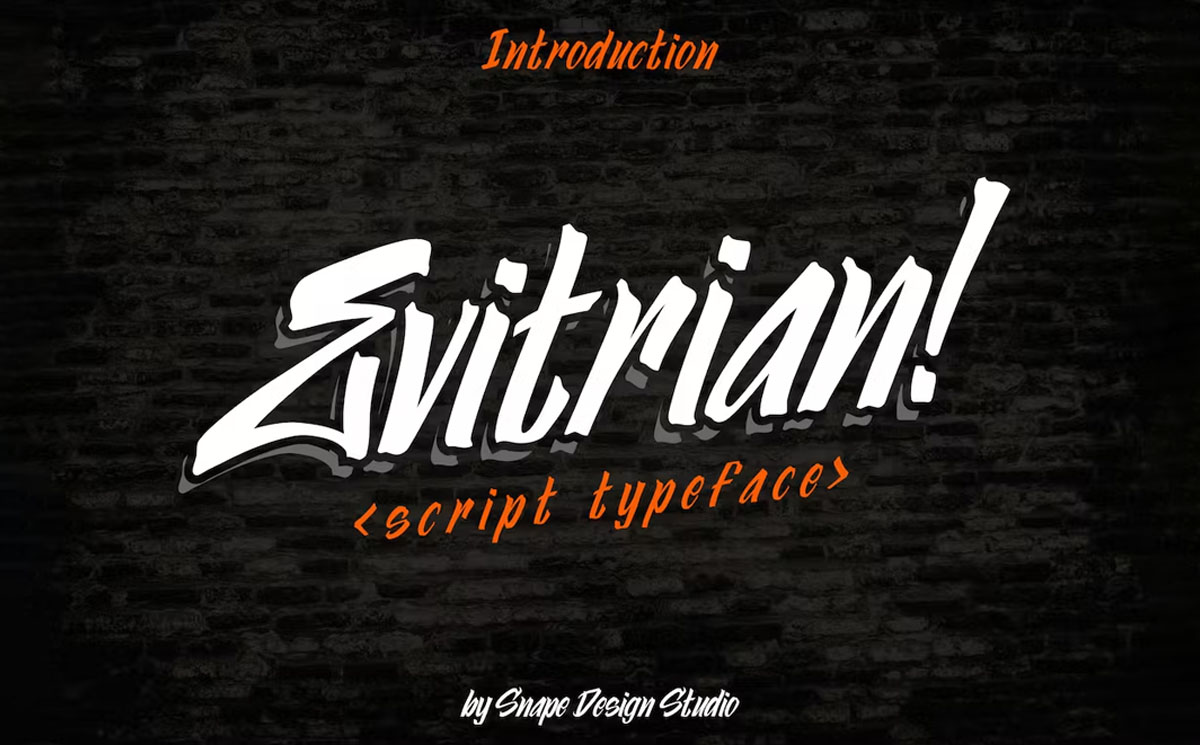
Phông chữ hiphop Việt hóa SVN Evitrian
Phông chữ HipHop Việt hóa SVN Evitrian – Cá tính, mạnh mẽ và đậm chất đường phố
Nếu bạn đang tìm kiếm một font chữ mang phong cách HipHop, Graffiti và Street Art, SVN Evitrian Việt hóa là lựa chọn rất đáng thử. Bộ font gây ấn tượng với những đường nét mạnh, phá cách và giàu năng lượng, phù hợp cho các thiết kế cần tạo cảm giác nổi bật ngay từ cái nhìn đầu tiên.
SVN Evitrian – Font chữ đậm chất HipHop đường phố
SVN Evitrian sở hữu phong cách typography cá tính với các nét chữ độc đáo, mang hơi hướng HipHop, Urban và văn hóa đường phố. Kiểu dáng chữ mạnh mẽ giúp thiết kế trở nên trẻ trung, nổi loạn và có chất riêng hơn so với những font thông thường.
Phiên bản SVN Evitrian Việt hóa hỗ trợ tiếng Việt đầy đủ, giúp designer dễ dàng sử dụng các dấu tiếng Việt mà vẫn giữ được phong cách nguyên bản của font.
SVN Evitrian phù hợp với thiết kế nào?
Font đặc biệt thích hợp sử dụng cho:
• Poster HipHop, Rap và Underground.
• Thumbnail YouTube, TikTok, Facebook.
• Banner sự kiện âm nhạc.
• Artwork Rapper, DJ và nghệ sĩ.
• Thiết kế áo thun Streetwear.
• Logo và branding phong cách Urban.
• Bìa album, mixtape và playlist.
• Graffiti Typography.
• Poster game hoặc thiết kế phong cách Cyber Street.
Với những tiêu đề kích thước lớn, SVN Evitrian có khả năng tạo điểm nhấn rất tốt và giúp nội dung trở nên dễ nhận diện hơn.
Điểm nổi bật của font SVN Evitrian Việt hóa
Phong cách HipHop mạnh mẽ: Kiểu chữ mang tinh thần đường phố rõ nét, phù hợp với những sản phẩm sáng tạo dành cho giới trẻ.
Hỗ trợ tiếng Việt: Phiên bản Việt hóa giúp nhập đầy đủ các ký tự và dấu tiếng Việt thuận tiện hơn trong quá trình thiết kế.
Dễ tạo Typography: Chỉ cần kết hợp font với texture graffiti, hiệu ứng chrome, neon, spray paint hoặc background đô thị là có thể tạo ra những artwork rất bắt mắt.
Gợi ý phối SVN Evitrian đẹp hơn
Để phát huy đúng chất của SVN Evitrian, bạn có thể kết hợp font với các gam màu như đen, đỏ, vàng neon, xanh electric, tím hoặc bạc chrome.
Background có thể sử dụng tường graffiti, đường phố ban đêm, texture bê tông, ánh sáng neon hoặc hiệu ứng spray paint để tăng thêm cảm giác HipHop và Underground.
Tổng kết
Phông chữ HipHop Việt hóa SVN Evitrian là một lựa chọn thú vị dành cho những ai yêu thích phong cách HipHop, Rap, Graffiti, Streetwear và Urban Design. Với hình dáng chữ cá tính cùng khả năng hỗ trợ tiếng Việt, font rất phù hợp để tạo poster, thumbnail, banner, artwork âm nhạc và nhiều sản phẩm thiết kế mang phong cách đường phố.
Nếu bạn đang muốn tạo một thiết kế chất, nổi bật và đậm tinh thần HipHop, SVN Evitrian chắc chắn là font đáng có trong bộ sưu tập của mình.